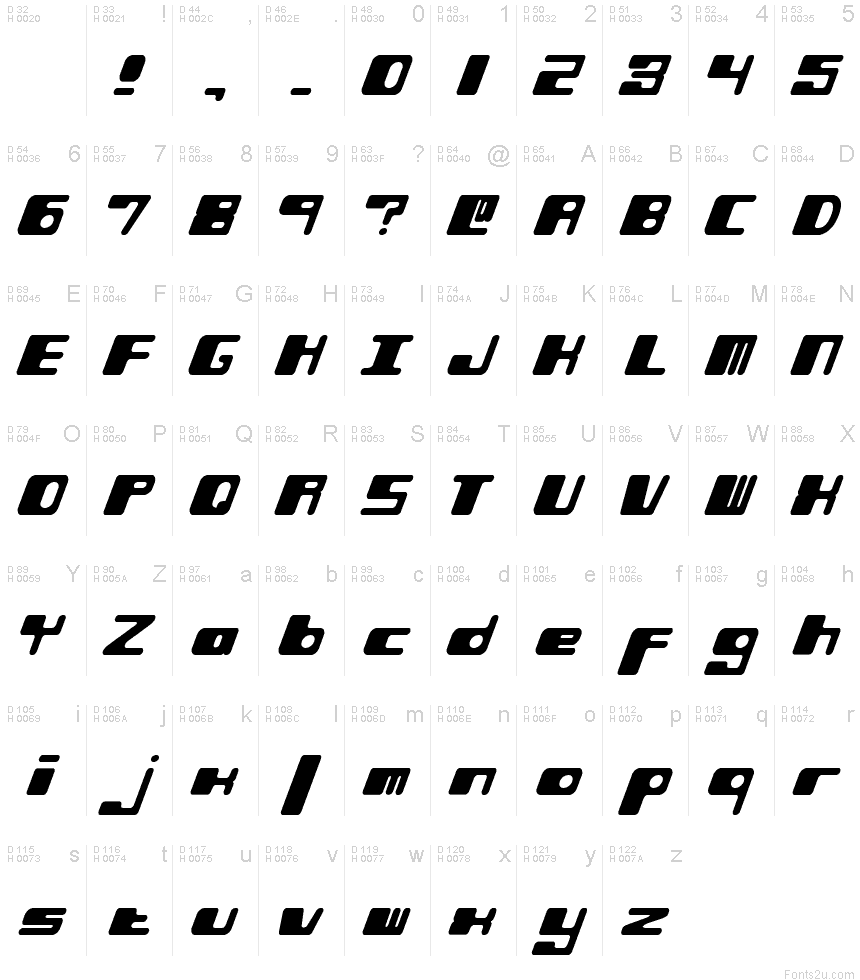
Phorfeit di ÆNIGMA Fonts è un font display futuristico gratuito, dal carattere rapido e dinamico. Le lettere puntano su angoli arrotondati e giunzioni tagliate, mescolando tratti robusti a tagli aerodinamici che fanno sembrare il font uscito direttamente da una moto concept o da un cruscotto arcade.
Si adatta perfettamente a loghi di gaming, poster tech, copertine di album, titoli e brand dove il movimento conta più della formalità. Essendo un font gratuito, Phorfeit dà il meglio di sé in titoli compatti, grafiche a badge e monogrammi, perché quelle forme larghe e scolpite mantengono una forte spinta in avanti anche con poche lettere.